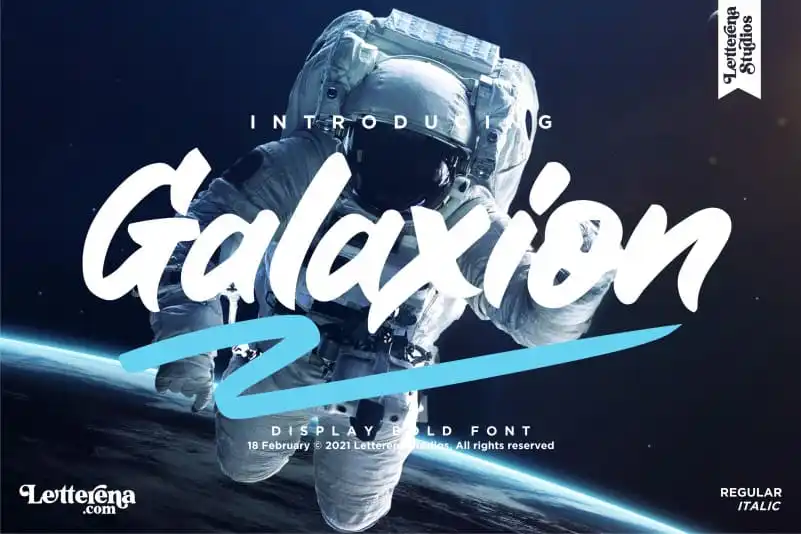
Galaxion Font é uma elegante tipografia brush que traz personalidade para projetos visuais variados. Seu estilo robusto e vibrante a torna perfeita para carregamentos de design, desde logotipos até embalagens de produtos, passando por posters, ilustrações e designs em papel. Suas linhas fortes podem enriquecer qualquer projeto que seja sobre expressar um estilo único e sofisticado. Designada especificamente para aplicações como identidade visual (logomarcas), embalagens e design gráfico de produto, Galaxion Font se destaca ao mesmo tempo em projetos mais tradicionais, como cartões de visita ou folders empresariais. Suas capacidades versáteis e sua personalidade vibrante a tornam uma escolha inteligente para designers que buscam um estilo autêntico e elegante em seus trabalhos. Com Galaxion Font, os criadores da letraenastudios estão oferecendo aos artistas gráficos, designer de marca e empresas inovadoras uma maneira visualmente atraente de apresentar suas ideias. Sem dúvida, é um recurso indispensável para qualquer trabalho que deseja destacar-se na cena digital atual com uma identidade visual forte e única.